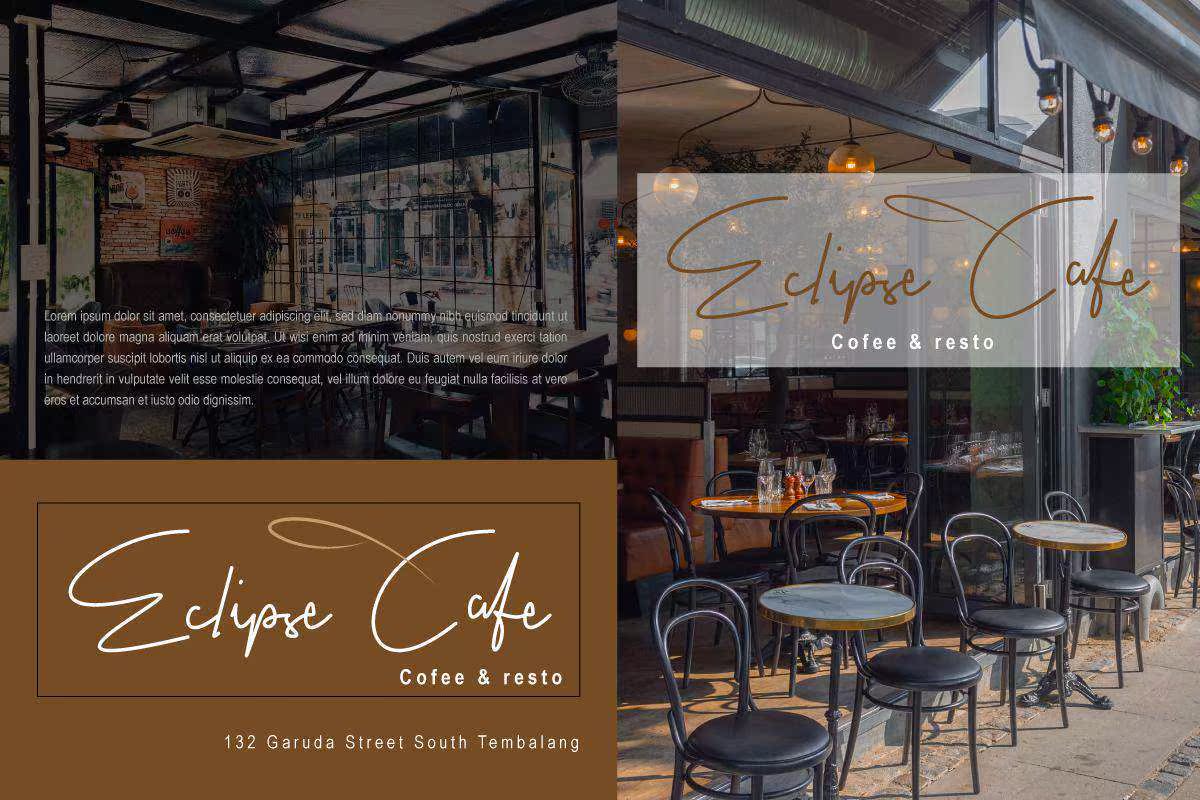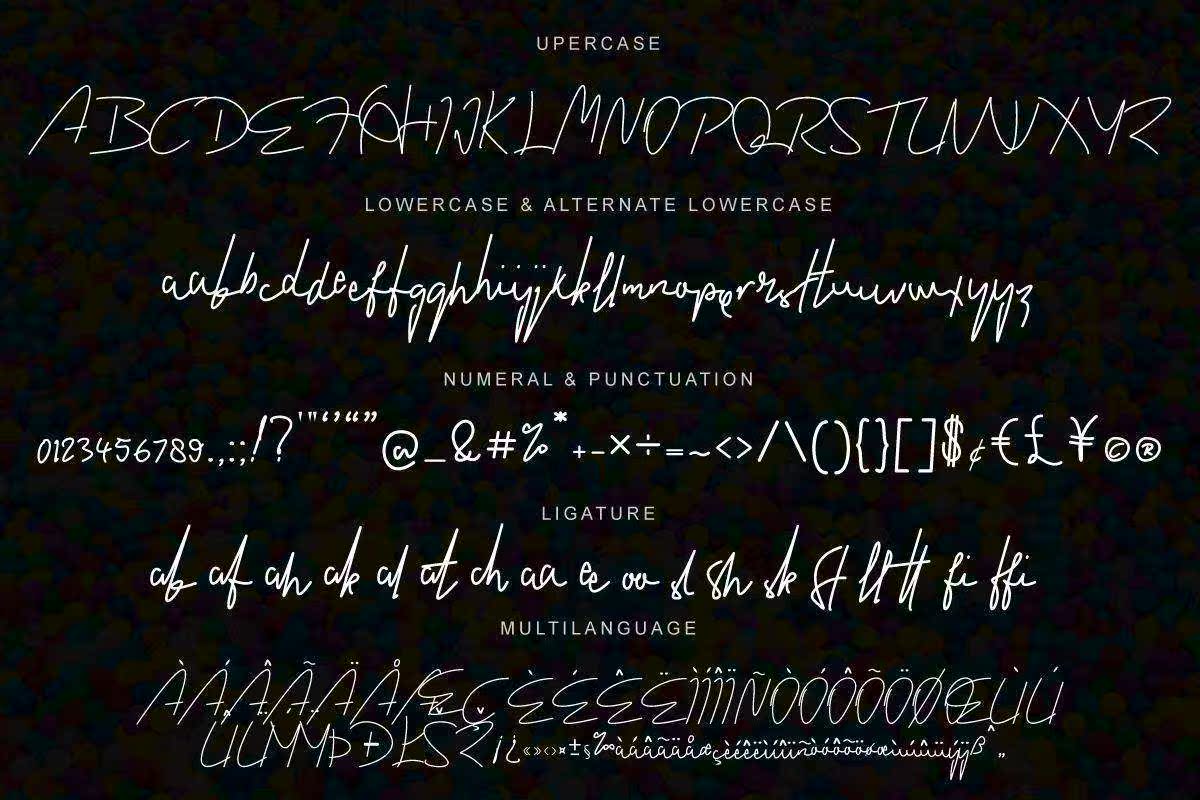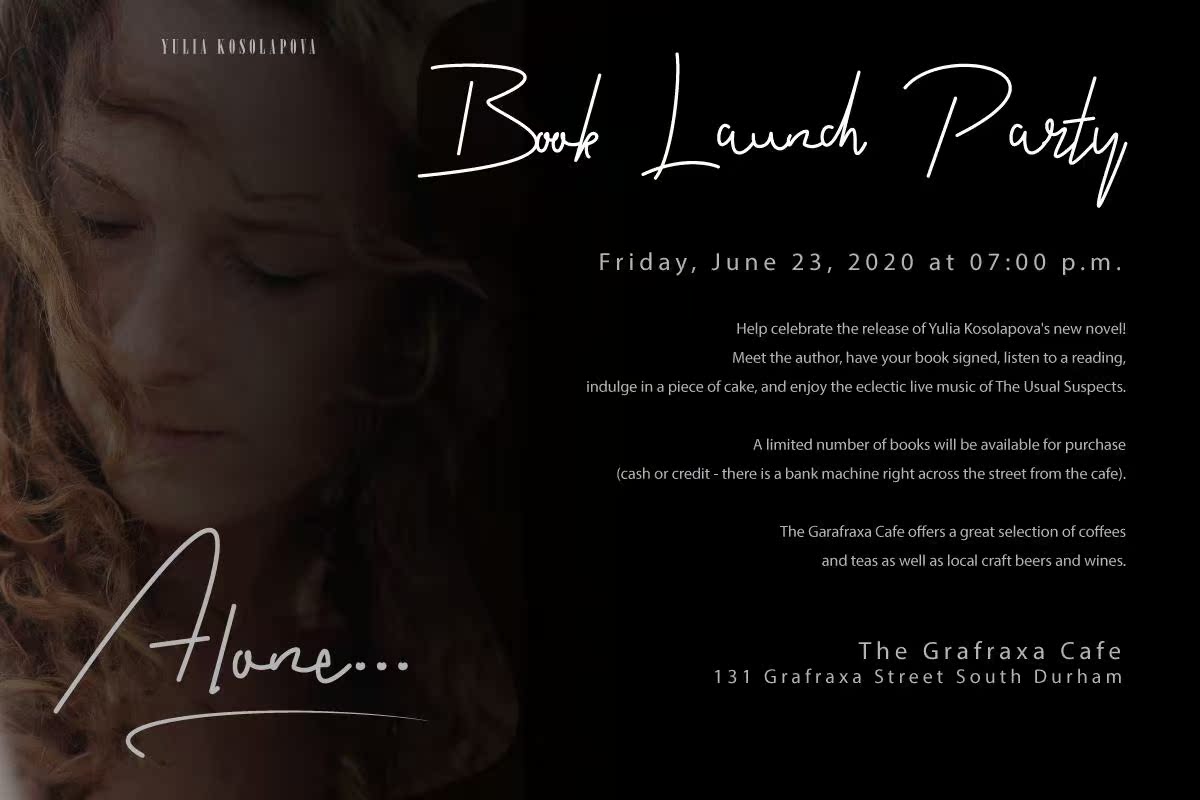
Childish Signatures A和Writen Monoline采用签名风格,简单但优雅。Childish Signatures可用于书名、报价、婚礼宣传、平面设计、印刷设计、网站设计、品牌等多种用途。Childish Signature A和Writen Monoline采用签名风格,简单但依然优雅。童稚的签名可用于各种用途,如书名、报价、婚礼宣传、平面设计、版画设计、网页设计、品牌推广和许多其他用途。